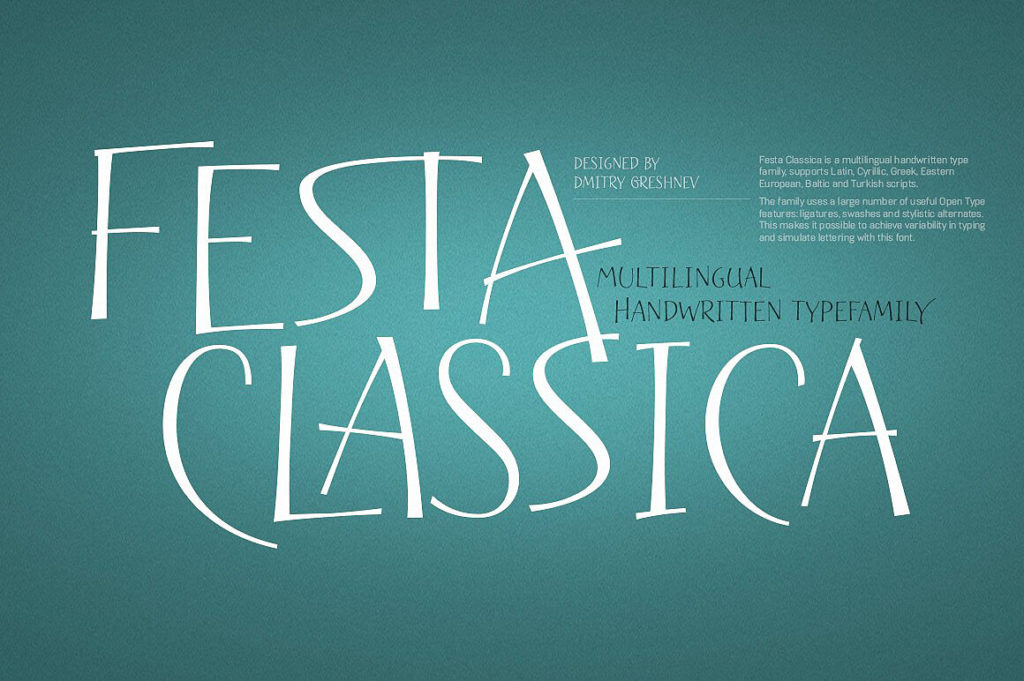
Шрифт Festa Classica Family
Шрифт Festa Classica — это многоязычное рукописное семейство от дизайнера Дмитрия Грешнева, выпущенное словолитней Green Type в декабре 2017 года. Гарнитура представляет собой элегантный каллиграфический шрифт, который сочетает праздничную энергию с изысканной классической утончённостью. Благодаря поддержке кириллицы, латиницы, греческого и многих других алфавитов, шрифт отлично подходит для русскоязычных проектов, где требуется изысканный и нарядный стиль. Если вы ищете шрифт для праздничных мероприятий и событийного дизайна, вы можете скачать его для ознакомления прямо с этой страницы.